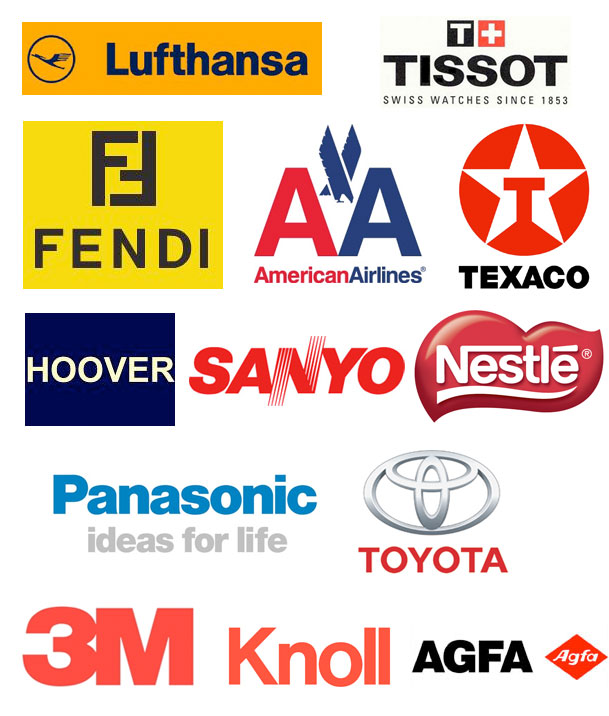
Cuando daba clases de diseño, algunos de mis alumnos rechazaban tipografías como Univers, Gill, Futura, Frutiger o Helvetica en sus diseños. En cambio me insertaban cada adefesio que se les figuraba creativo que realmente retaban mi tolerancia. La prueba de fuego de cualquier tipografía es ¿Funciona en una columna de texto? Todas las que respondan sí son buenas tipografías; las que queden fuera son sólo moda y morirán como tal.
Ahora, de todas las tipografías ¿Cuál es la mejor? Si nos remitimos a la historia y a la usabilidad, Helvetica es la indiscutible reina. Baste ver la cantidad de logotipos diseñados con ella.
De modo que si has dejado de cometer outlines, shadows, bebels y otros pecados; si te sientes fascinado ante la simplicidad de un logotipo como 3M, prefieres los vectores a los pixeles y puedes citar en una conversación a Max Meidinger… pequeño saltamontes, estás listo: eres un Diseñador.